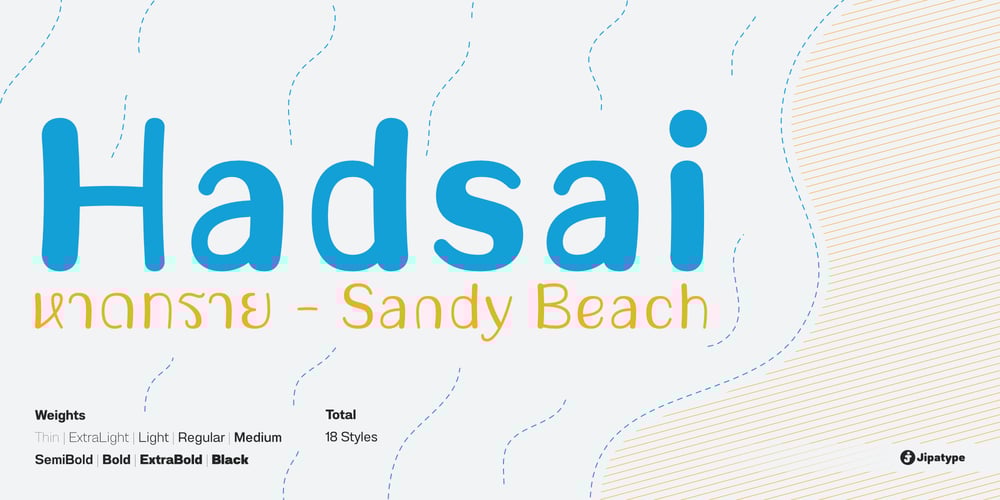
Hadsai Font Family was designed by Anupap Jaichumnan and published by Jipatype. Hadsai contains 18 styles and family package options. ฟอนต์ หาดทราย ลักษณะกลมมน เส้น Stem มีความหนาแตกต่างกันสองขนาด หนา-บาง ไม่เท่ากัน การเดินเส้นเลียนแบบลายมือ มาพร้อมกับฟีเจอร์ dlig ที่เปิดใช้งานแล้วจะยกตัวอักษรลำดับที่สองให้สูงขึ้นเล็กน้อยสลับกันเป็นฟันปลา เหมือนคลื่นเล็ก ๆ บนผิวน้ำ ให้ความรู้สึกเป็นมิตร น่ารักใสๆ มีไดนามิค สนุกสนาน ไม่เป็นทางการ เหมาะสำหรับการผาดหัว โปรยประโยคข้อความสั่น ๆ มีให้เลือกใช้ 9 น้ำหนัก ทั้งตัวตรงและตัวเอียงรวมเป็น 18 สไตล์-Hadsai, rounded shape, stem lines are of two different thicknesses, look like handwriting. It comes with a dlig feature that is enabled to raise the letter to zigzag. Like a wave on the surface of the sea water, it feels friendly, cute, clear, dynamic, fun, casual. Suitable for headline and sub-headline. Available in 9 weights, both upright and italic, total of 18 styles.